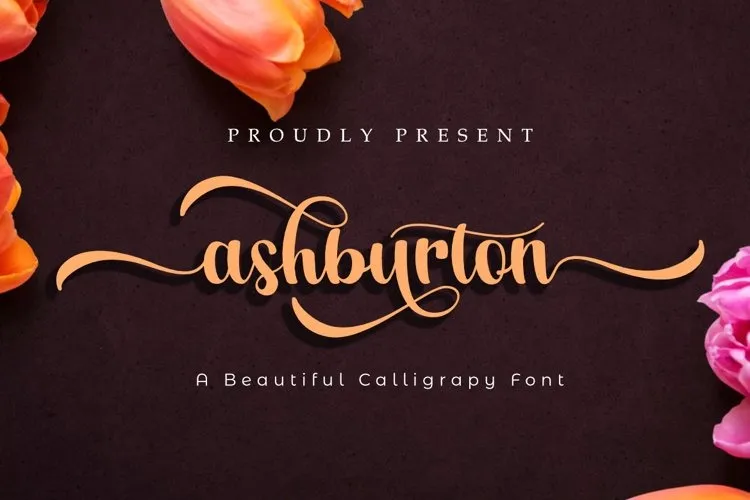
Ashburton Font
Ashburton Font é uma elegante e moderna tipografia script criada para aqueles que buscam um estilo que transmite sofisticação ao mesmo tempo em que traz a mão à sua arte, tornando-a perfeita para um amplo leque de projetos gráficos. Suas linhas fluidas e seu charme clássico são ideais para o design de cartões de casamento, cartões de agradecimento, mensagens pessoais, cartazes de boas-vindas, logomarcas, cartões de visita e qualquer outro projeto que necessite daquela sensação única e autêntica do texto escrita à mão. Sua versatilidade faz Ashburton Font um escolha perfeita para designers em busca de uma fonte de qualidade que não se limita a apenas um único uso, mas sim ao revolucionar inúmeros estilos e formatos gráficos.